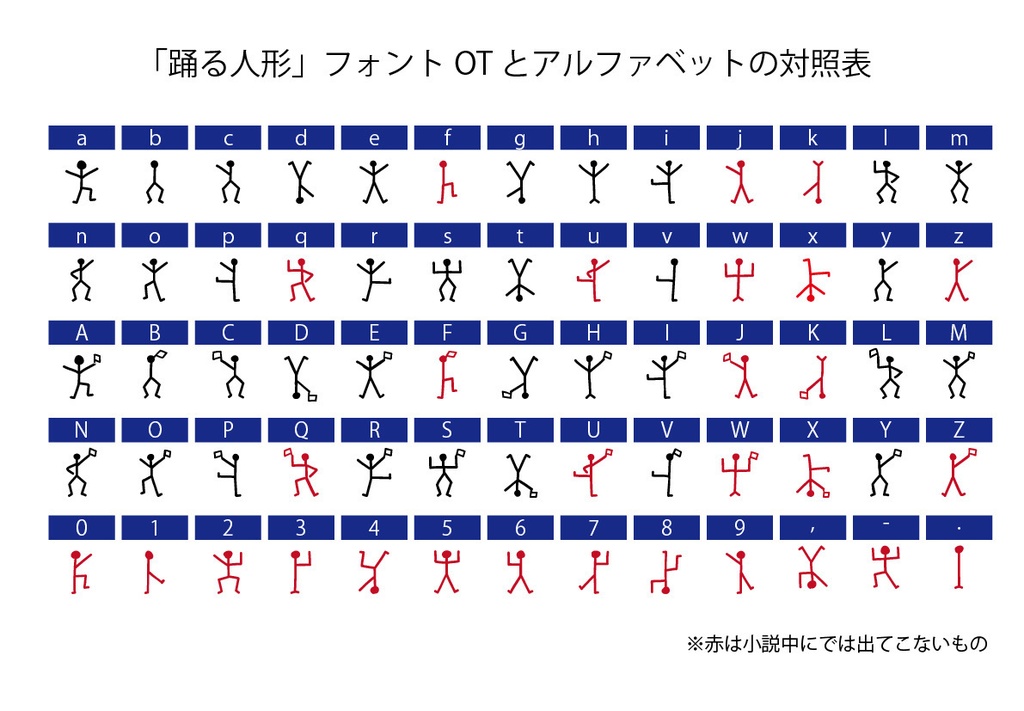
デジタルコンテンツ シャーロック・ホームズ「踊る人形」フォントOT
シャーロック・ホームズシリーズの短編「踊る人形」(The Dancing Men)に出てくる暗号を模した手書き風フォントです。 「踊る人形」はコナン・ドイル「シャーロック・ホームズ」シリーズの短編「踊る人形」の中で使われる暗号。腕や脚を上げたシンプルな人形の絵で描いています。 小説では英語アルファベット1文字1文字を対応する人形の絵に置き換えています。この人形の形をそのままフォントにしました。 ただし作中には登場しない文字が8文字(FJKQUWXZ)あるので、これについてはpuikkoが創作しました。また、0〜9の数字、半角記号(,-.)についても創作しました。 なお、小説では単語の区切りを表すために語尾の人形に旗をもたせていますが、このフォントでは大文字を旗をもった人形にしています。 フォントファイルの形式はOpenTypeファイルです。 MacOS VenturaとWindows11での動作確認はしています。 【収録文字】 英語アルファベット(A〜Z、a〜z)、数字(0〜9)、半角記号(,-.) 【データ内容・使用方法】 zipファイルを解凍してください。 OpenTypeファイル pkDancingMen.otf JPGファイル(「踊る人形」とアルファベットの対照表) comparison.jpg テキストファイル readme.txt が収録されています。 pkDancingMen.otfをインストールしてください。 【購入の際の注意点】 商用利用OKです。 使用した場合、ご一報いただけるとうれしいです。Twitterなどで紹介します。 フォントファイルの改変・再配布は禁止です。